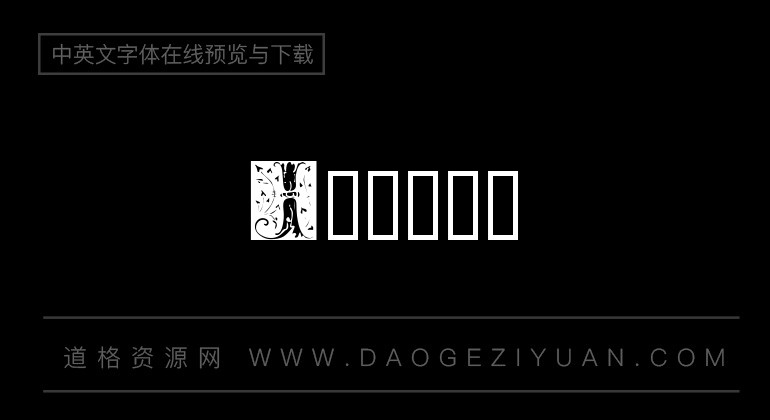
Jugend
Jugend字体(也称为Art Nouveau字体)是一种艺术风格的装饰性字体,起源于19世纪末的德国,主要用于宣传海报、书籍等印刷品的设计中。Jugend字体的特点是精细而优美的线条、流畅的轮廓和华丽、充满装饰性的字形。它们通常被设计成弯曲的花卉、叶子、藤蔓、蝴蝶等自然图案,或者是曲线、波浪、地球等抽象图案。Jugend字体广泛应用于欧洲艺术风格的设计中,在当时的艺术领域具有很高的地位和影响力。
Jugend是一款非常不错的手写艺术字体,具有很好的视觉感,适合于文化类的宣传设计、商业类品牌的广告和产品包装设计以及个性化文字排版等较多场景。